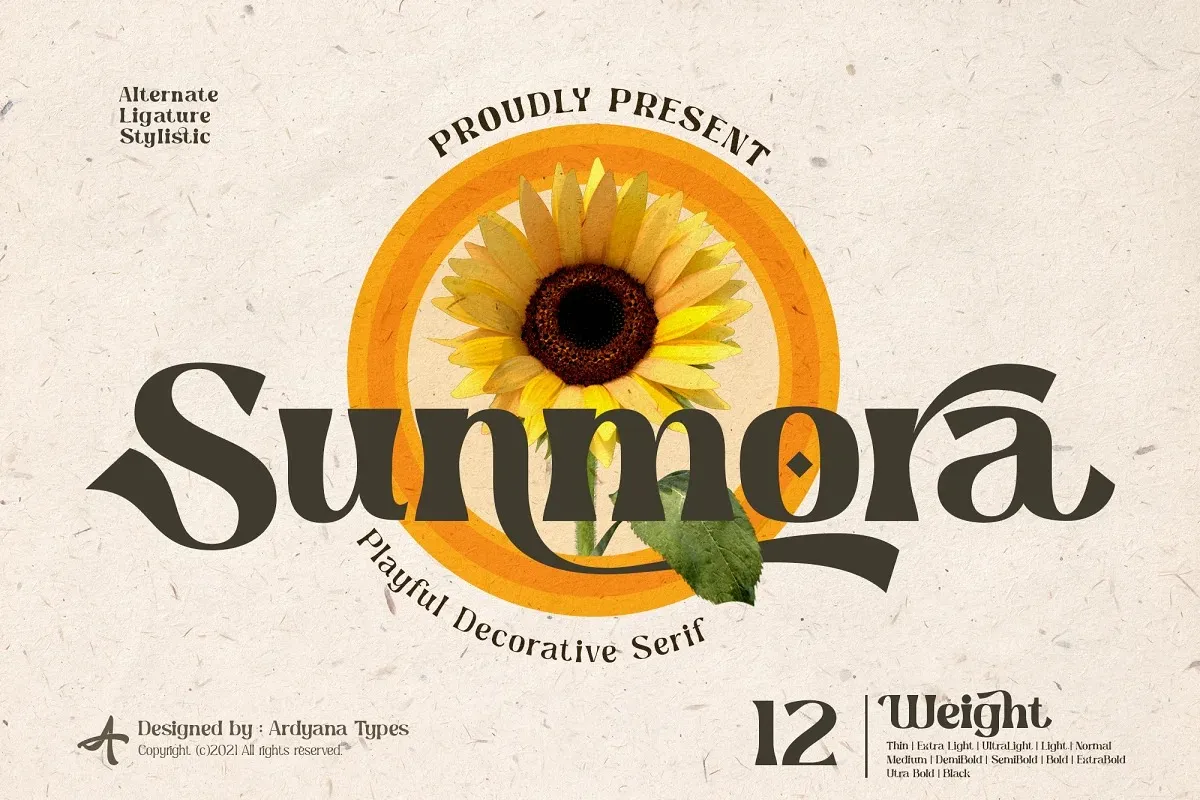
Sunmora Font – Download Grátis
A Sunmora Font é uma elegante serif display que transmite beleza e suavidade. Desenvolvida no estilo dos serif fonts classicamente decorativos dos anos 80 até os dias atuais, essa fonte leva ao espectador um sentido de sofisticação e modernidade combinada, perfeita para ambientes de design gráfico requintados. Com sua estrutura elegante e linhas suaves, a Sunmora Font é uma escolha ideal para criar visuais arquitetônicos memoráveis que capturam a essência de um design sofisticado e sofisticado. Seja em banners de mídia social ou capas de livros, esta fonte oferece o estilo necessário para deixar seu trabalho impecável.